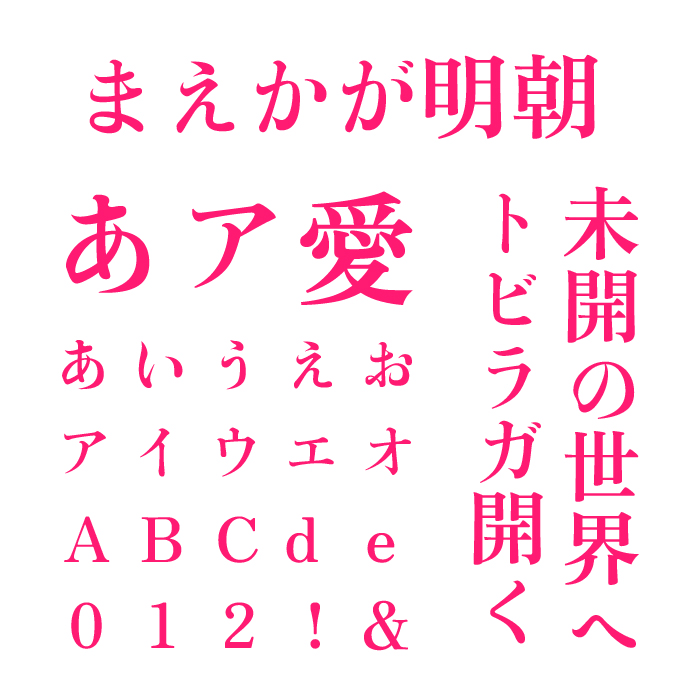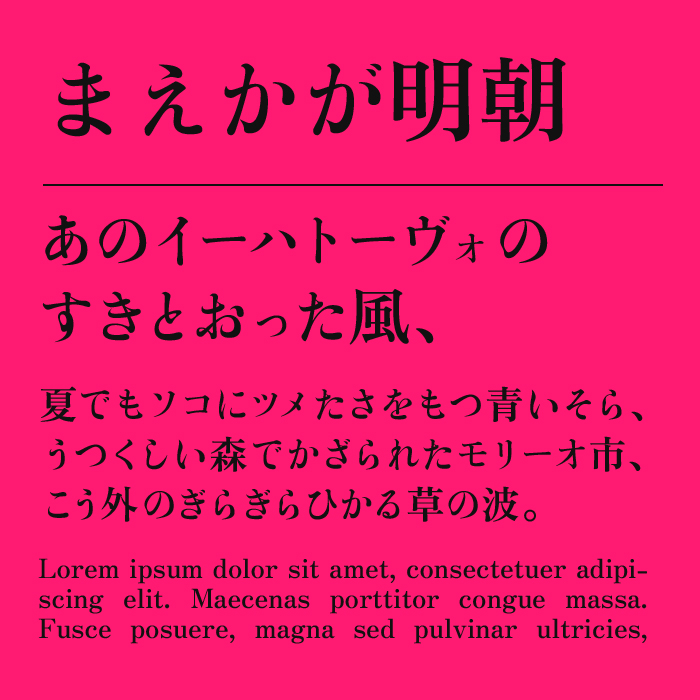
まえかが明朝フォントは、「もじくみ仮名」と「ZENオールド明朝(Bold)」を混植して制作された、どこかクラシカルな香りを残しつつも、現代的な可読性を備えたオールド系明朝体です。
ゆるやかに左へ傾いたフォルムが特徴で、文章全体に独特の流れとやわらかさを与えています。力強さよりも繊細さや知性が際立ち、品のある印象です。
硬すぎない明朝体として、詩やエッセイ、文学的なコンテンツとの相性が抜群なフォントです。また、読み手に柔らかな余韻を残すため、広告や雑誌の本文にもぴったりな明朝体です。